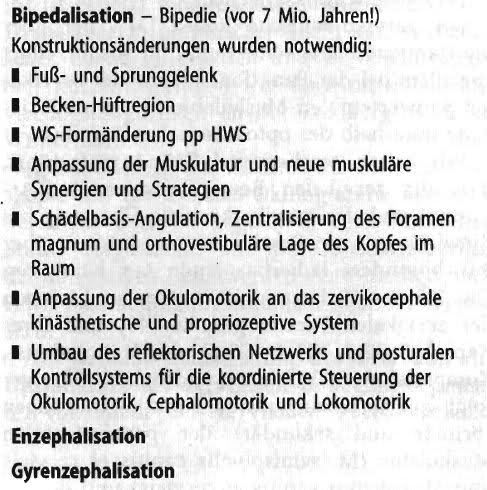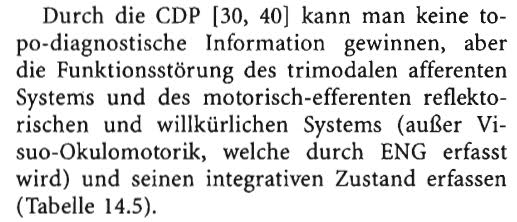
Bitte um Hilfe (schlechter Scan)
Um welche Schriftarten könnte es sich in etwa handeln?
Es ist ein Text aus einem Fachbuch:
M. Graf, Trier; C. Grill, Ramsau; H.-D. Wedig, Kanzlei, Sonthofen (Eds.): Beschleunigungsverletzung der Halswirbelsäule
Springer Verlag
Kann dann die andere evtl. die Minion sein?
Ich glaube schon. Man kann auf dem Bild zwar keine Details erkennen aber die Formen stimmen eigentlich mit der Minion überein.
Der Text im ersten Scan dürfte in der Myriad condensed gesetzt sein.
Ich widerspreche, das ist mit Sicherheit die Frutiger Condensed:
Da liegst du mit großer Sicherheit falsch. Sieh dir nur die Schlaufe beim "a" an: die setzt - typisch für viele Schriften von Adrian Frutiger - bei der Frutiger völlig horizontal am Schaft an, im vorgelegten Scan aber ganz und gar nicht. Und weitere Abweichungen ...
Der Springer-Verlag hat eine eigene, angepasste Schriften, die auf der Myriad Condensed und der Minion basieren. War jedenfalls vor einiger Zeit noch so, als ich für den Verlag die Templates in Word gemacht habe. Steht jedenfalls so im Handbuch zur CI.
Leider scheint Springer inzwischen vollständig auf Adobes OpenType-Schriften umgestellt zu haben. Das ist ein Jammer, denn die Springer-Minion ist viel besser lesbar.